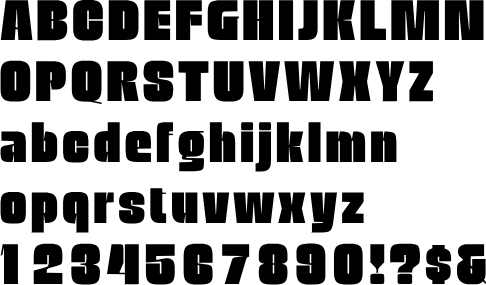
VGC ( Visual Graphics Corporation ) よりリリースされたレア
書体「ネイル・ボールド」。
ところどころに切り込みが入っており、ポップでありながらエッジーな、なんとも不思議な魅力があります。
このフォントからインスパイアされた「Mobley」というフォントもあります。
Neil Bold |
Designers |
Wayne J. Stettler |
Year |
1966 |
Foundry |
VGC |